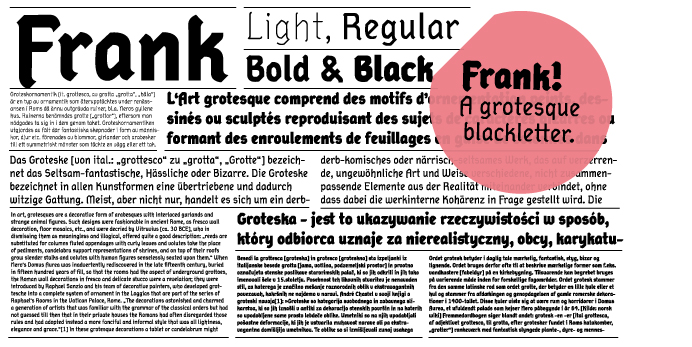
Frank is a hybrid sans serif blackletter font. Graphic designer Anton Studer has adapted blackletter script lettering, also known as Gothic script, used in German-speaking countries until the late 20th century into a contemporary sans serif font with character. This no frills font can be used in small point sizes as well as used in larger headlines. Available in three packages: Frank, Frank Central European and Frank Pro.
Auch auf die Gefahr hin, daß Ihr mich schlagt: Das »A Grotesque Blackletter« erinnert mich ganz ausnehmend an Comic Sans … :twisted:
holla, sowas unruhiges hab ich lange nicht gesehen. Das piekt und zwickt überall in den Augen. Sogar in den Überschriften. Not my cup of tea.
Hm … das Konzept ist ja echt interessant, aber für mich funktionierts auch nicht :( schade irgendwie. Mein erster Gedanke war auch «autsch». Und so im PDF find ich einzelne Formen sehr spannend, allerdings nur einzelne und nur, wenn sie sehr groß und allein stehen.
Vor allem: Wenn es irgendetwas nicht ist, dann ein »no frills font«. Dann doch lieber Tannenberg. Die kann man wirklich als »no frills« bezeichnen.